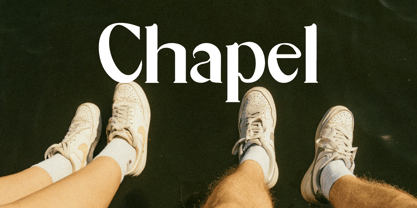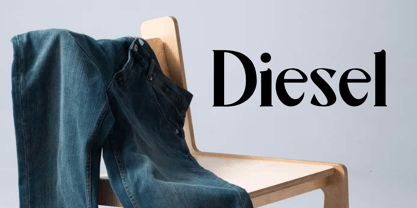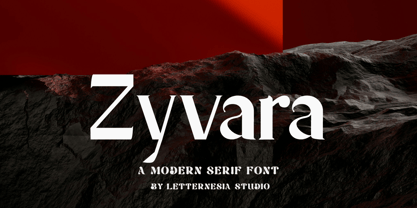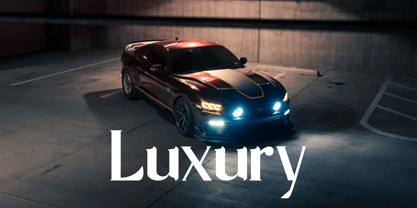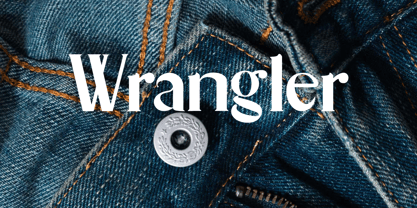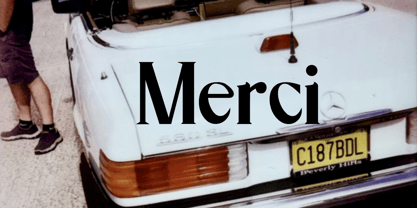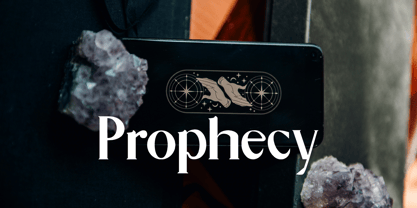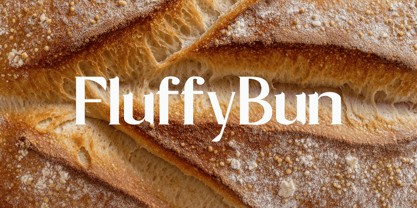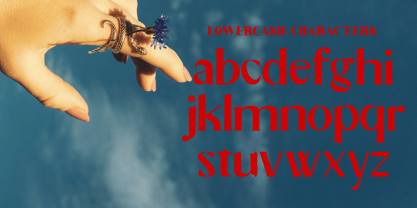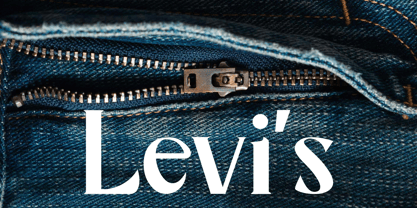
Zyvara
by Letternesia studio
The Zyvara Font Family was designed by Ta Siyo and published by Letternesia studio. Zyvara contains 2 styles and family package options.
Zyvara adalah font display modern yang dirancang untuk membuat setiap desain terlihat lebih berkelas dan menonjol. Dengan proporsi tegas, lekukan elegan, dan detail rapi, Zyvara menghadirkan kesan profesional sekaligus kreatif. Sangat ideal untuk logo, branding, poster, kemasan, undangan, hingga konten media sosial. Gunakan Zyvara ketika Anda ingin menciptakan tipografi yang menarik perhatian, meningkatkan nilai visual, dan memberikan kesan mewah pada setiap proyek.Elevate your work with Zyvara, a display font that combines visual strength with refined details. Perfect for branding, product design, editorial typography, and digital content, Zyvara adds a premium and professional touch. It ensures your projects stand out, leaving a memorable impression that feels both modern and timeless.
Letternesia is a company engaged in the creation and development of fonts, focusing on unique designs that highlight the distinct characteristics of Indonesia. Established with the goal of promoting and introducing Indonesian culture through typography, Letternesia offers a variety of fonts inspired by the beauty of the archipelago. Each font produced by Letternesia is crafted with high detail and precision, making it suitable for various needs, from graphic design and branding to other creative projects.